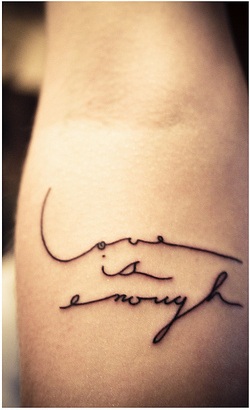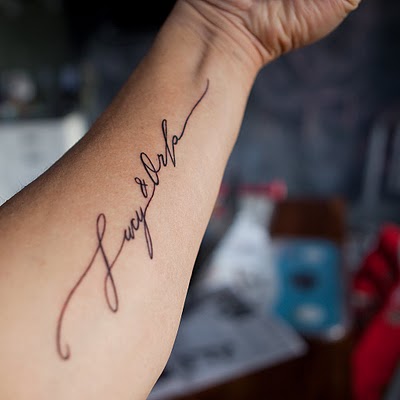
Handgeschriebene unbekannte Schrift?
Suche diese beiden unterschiedlichen Schriftarten, sehen handgeschrieben aus, aber vll gibt es sie ja doch :)
Spontan musste ich an die Schriften von Petra Beiße denken, dort sind die Minuskeln auch gesperrt gestaltet so zu sagen.
Sehr schön finde ich die Luxus Brut, die hat auch solche auseinandergezogenen Buchstaben:
Cool :-) Ist das 20er Jahre?
Luxus Brut breathes the spirit of hand lettered signage of the Fifties. It’s a formal script, inspired from a well concealed shop portal in Vienna/Austria. ...
Das mit den 50er Jahren glaub ich ja eben nicht. :-) Ich kenn mich aber in der Designgeschichte so gar nicht aus … :-?
Hmmm, bei der deutschsprachigen MyFonts-Seite gibt es das Bild der Vorlage zu sehen, nach welcher die digitale Schrift gestaltet wurde (Der Text sagt, dass das Schild aus der Nachkriegszeit stammt). Das sagt aber genau genommen auch nichts darüber aus, wann diese Schrift ursprünglich mal entworfen wurde. :-?
hm, irgendwie wirkt die gute auf mich sehr alt und edel :-)
Was sagt denn eigentlich der Fragesteller/die Fragestellerin zu den vorgeschlagenen Schriften? Ist da schon etwas Brauchbares dabei? Ich würde übrigens sagen, dass die Schriftzüge in den gezeigten Beispielen auf einer handgeschriebenen Vorlage basieren.
"Luxusbrut" sieht dem, was ich suche, wirklich schon sehr ähnlich!!
"Petra Beiße" passt total zum zweiten Bild, finde ich!
Cool :-) Ist das 20er Jahre?
Die Schrift ist sicher auch von der Kurrent beeinflußt. Die hat nicht nur ähnliche senkrechte Verhältnisse (2:1:2), sondern manchmal auch recht große Buchstabenabstände (wenn ich auch ein Beispiel mit so großen Abständen wie bei der Luxus Brut noch nicht gesehen habe).